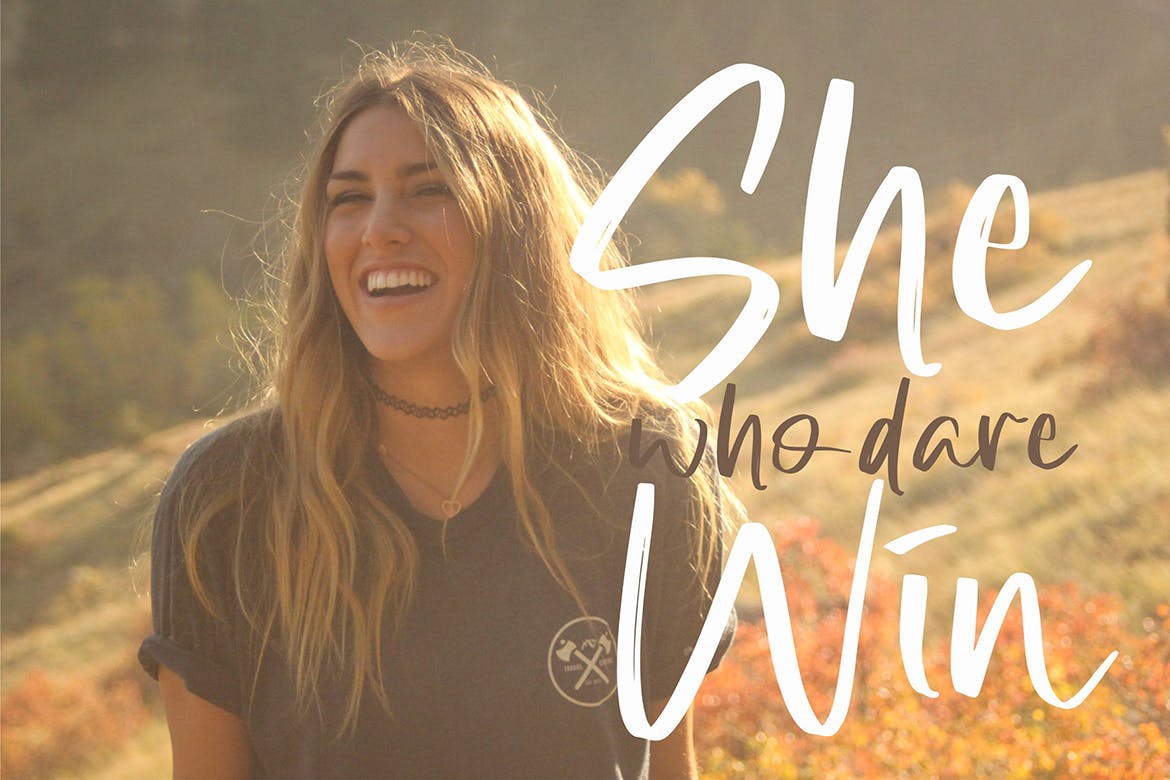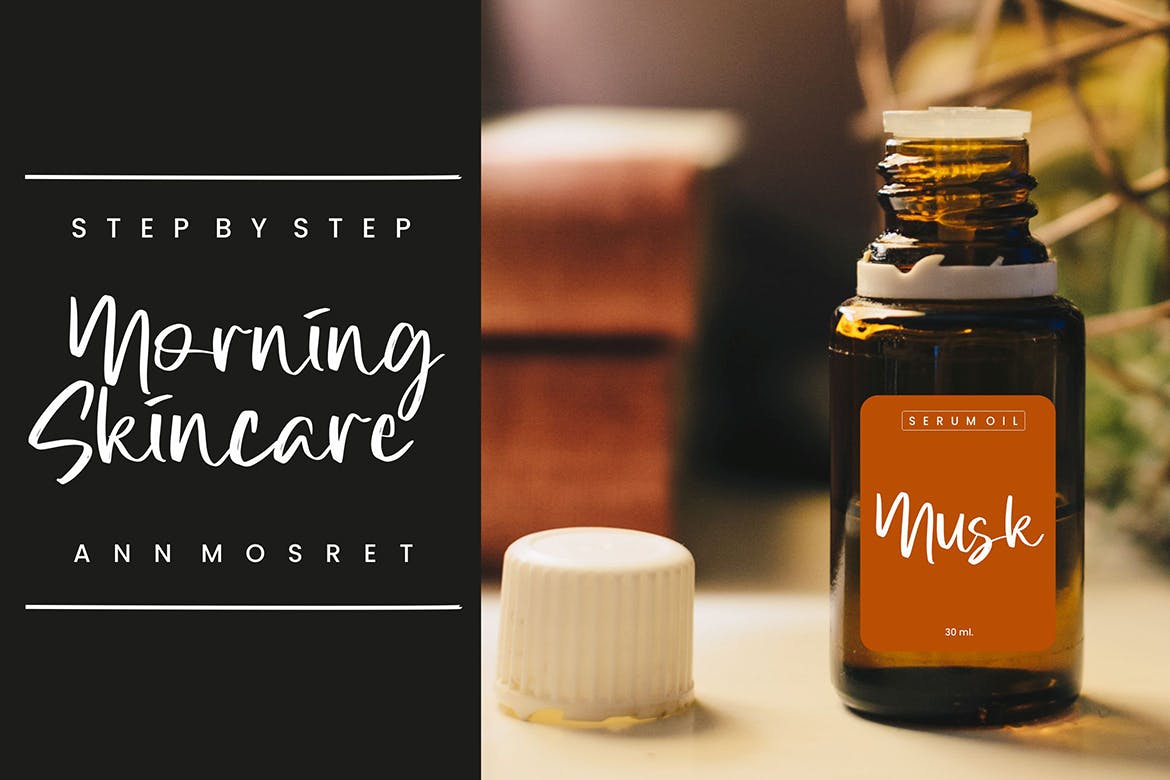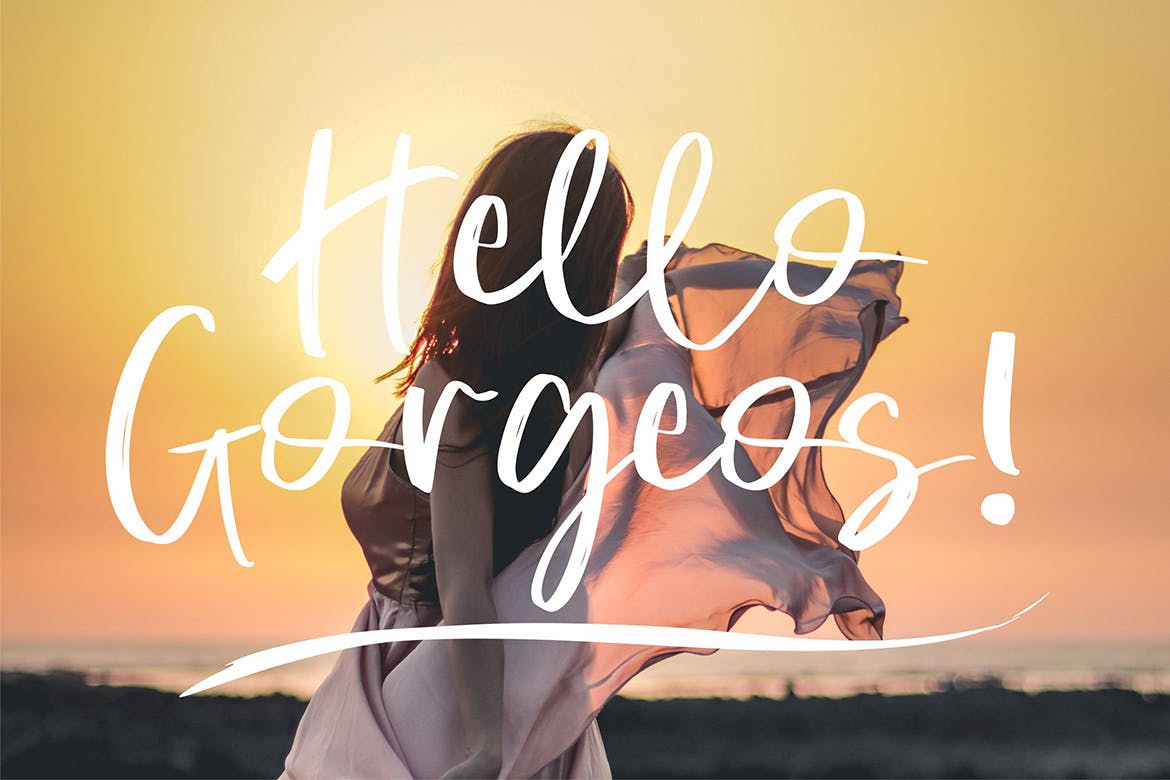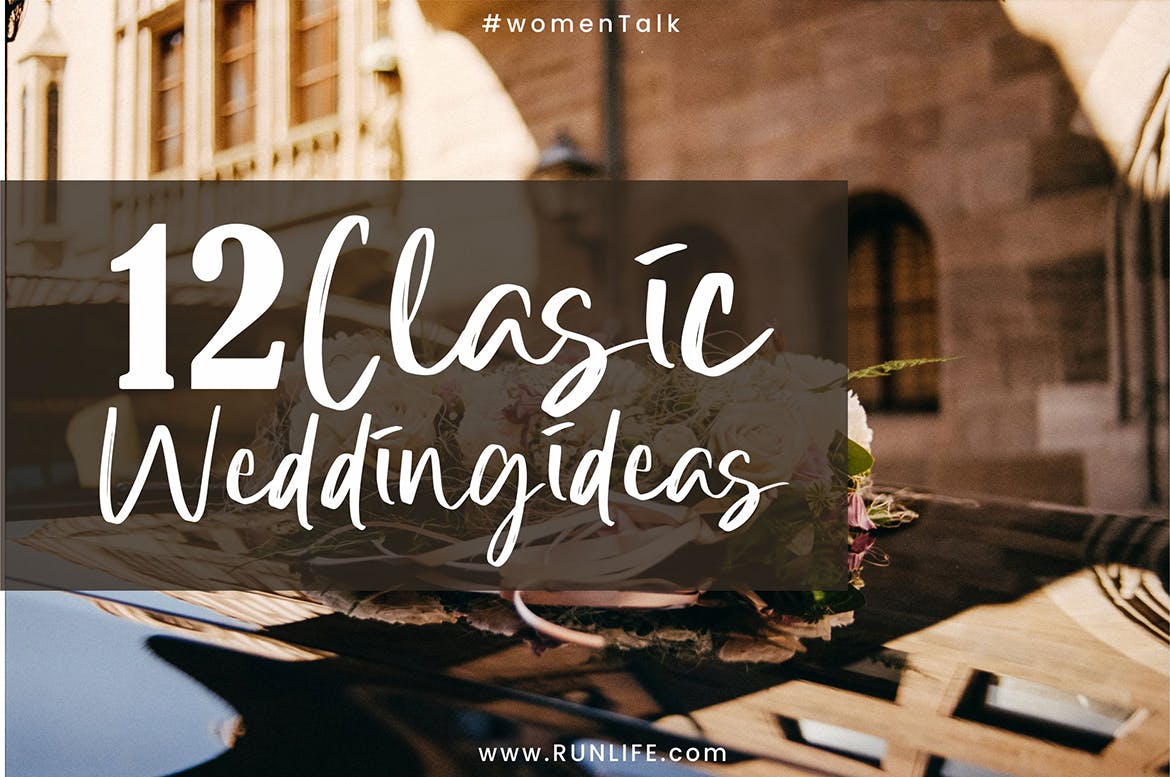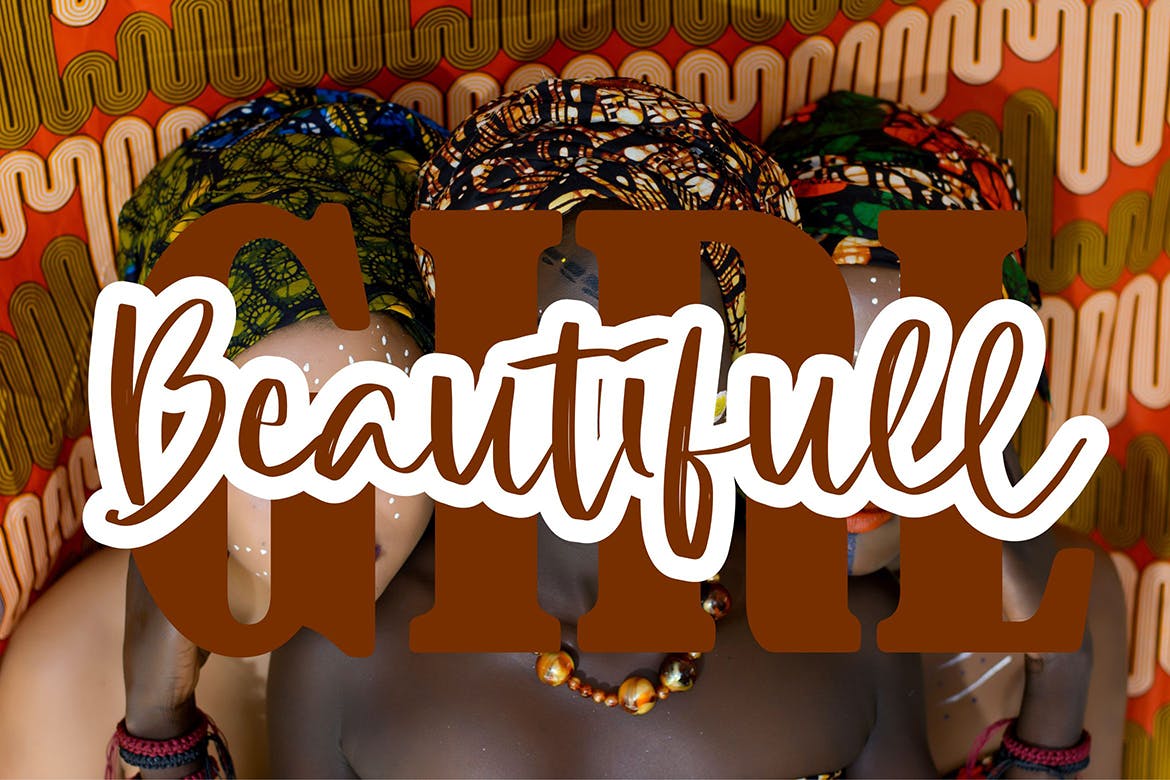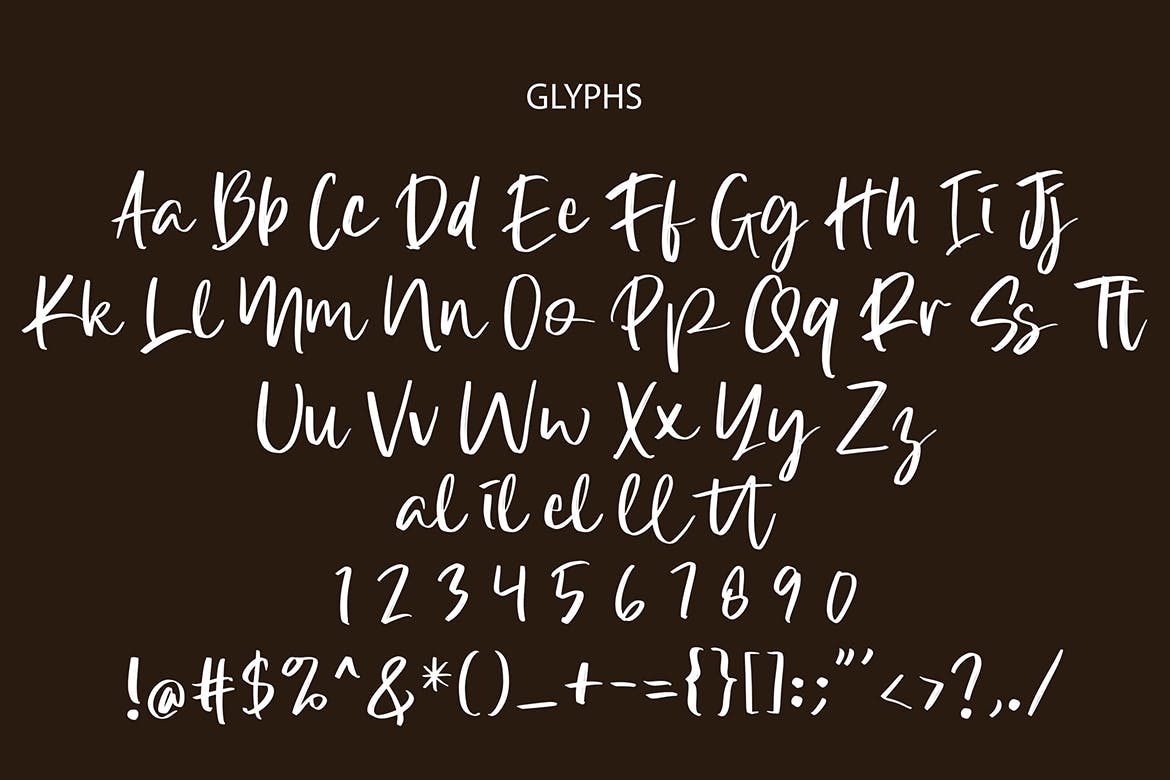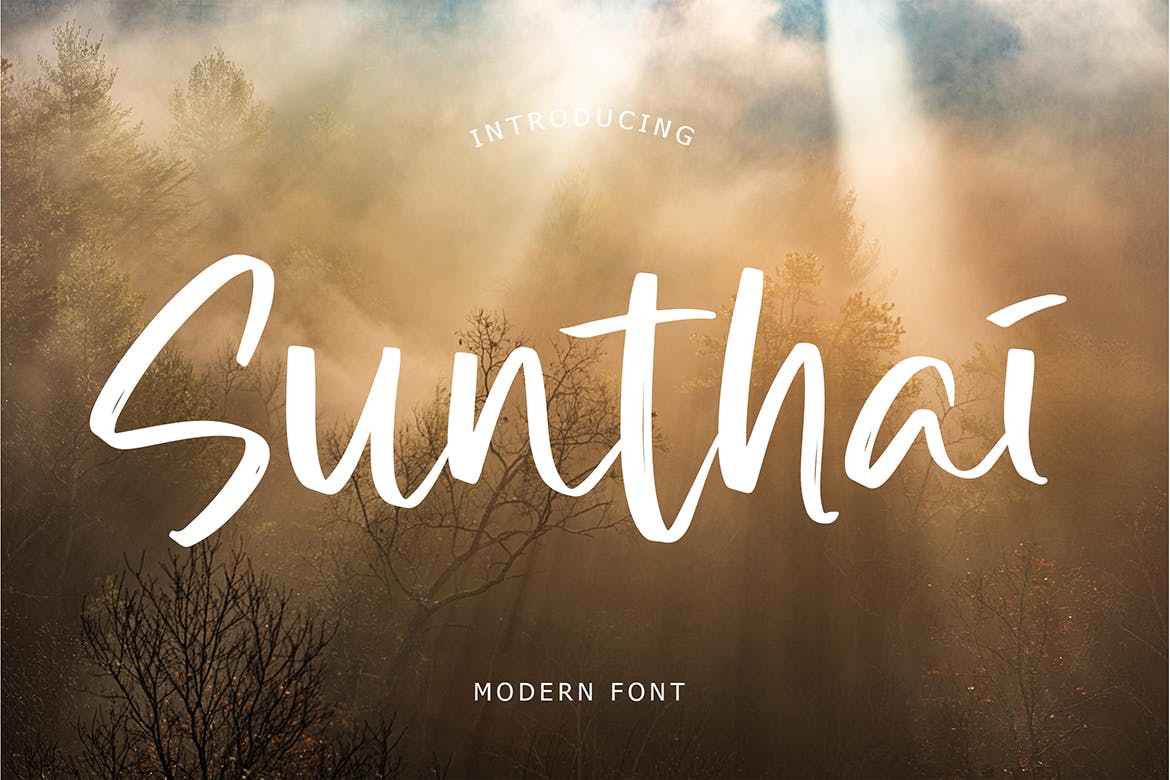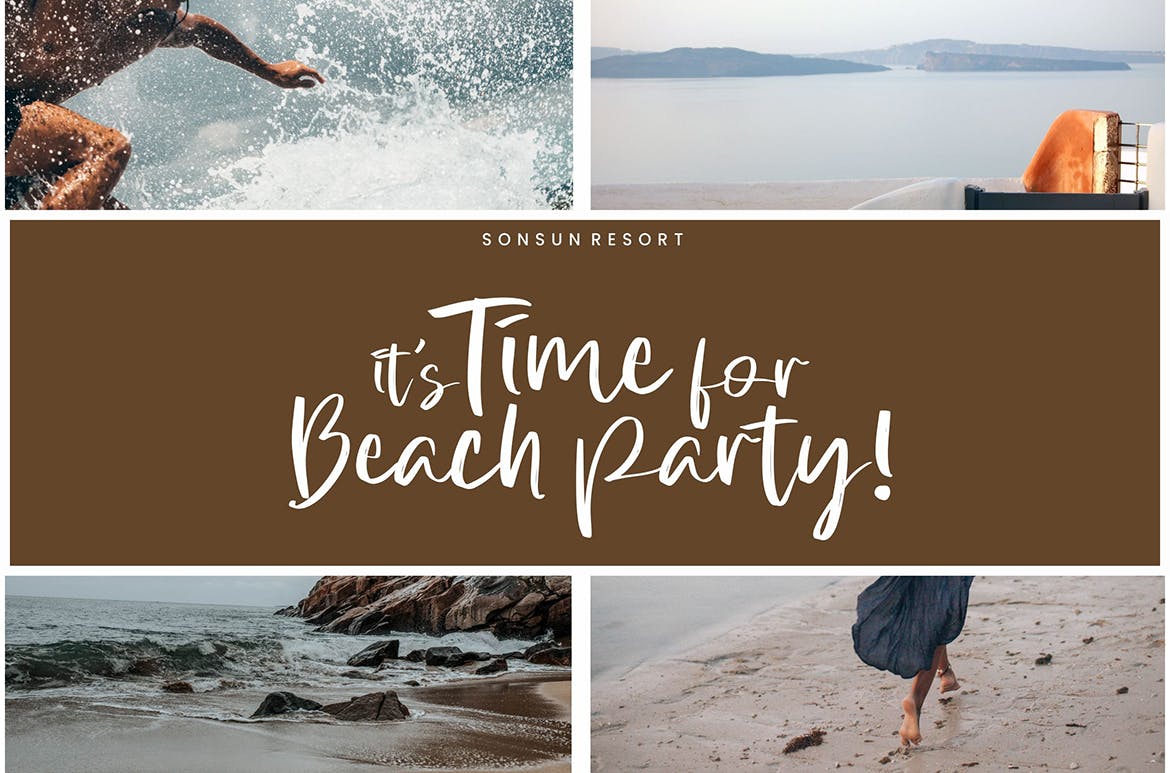
Sunthai Modern Font
فونت مدرن سانتای با سبک قلمو، انتخابی ایده‌آل برای پروژه‌های طراحی شما.
سانتای یک فونت مدرن با سبک قلمو است. این فونت برای پروژه‌های برندینگ، طراحی لوگو، طراحی تیشرت، پست‌های شبکه‌های اجتماعی، تبلیغات، بسته‌بندی محصولات، طراحی محصولات، برچسب، واترمارک، دعوت‌نامه، لوازم‌التحریر و هر پروژه‌ای که نیاز به زیبایی و خلاقیت دارد، مناسب است.
• لیگاتور